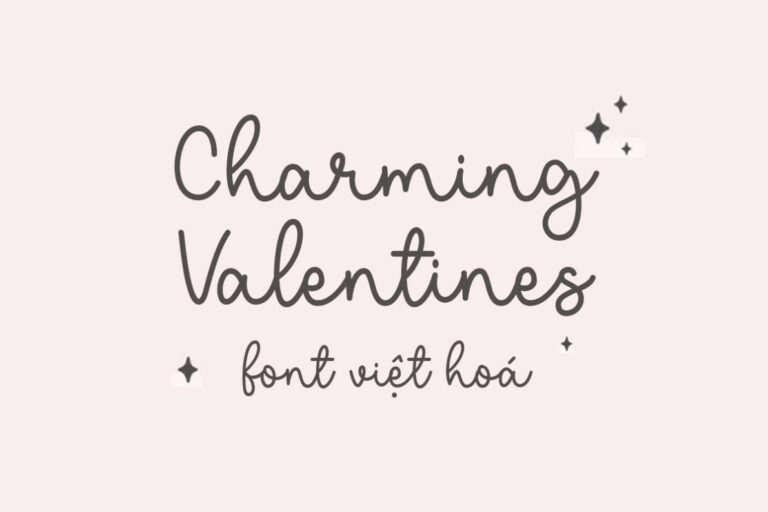
Tải Font việt hoá MJ Charming Valentines Tuyệt Đẹp Cho Thiết Kế Lãng Mạn
Giới thiệu về Font việt hoá MJ Charming Valentines
Trong thế giới đồ họa hiện nay, việc tìm kiếm một mẫu Font Chữ phù hợp để truyền tải thông điệp yêu thương là vô cùng quan trọng. Font việt hoá MJ Charming Valentines là một bộ font calligraphy hiện đại với những đường nét thanh mảnh, uốn lượn đầy tinh tế. Đây là sự lựa chọn hoàn hảo cho các bạn học sinh, sinh viên và thầy cô giáo khi muốn tạo ra những tấm thiệp chúc mừng, bài thuyết trình hay các ấn phẩm trang trí nhân dịp lễ tình nhân hoặc những sự kiện đặc biệt trong nhà trường.
Đặc điểm nổi bật của bộ font chữ
Bộ font này nổi bật với phong cách viết tay mềm mại, mang lại cảm giác chân thực và gần gũi. Điểm cộng lớn nhất là khả năng hiển thị tiếng Việt trọn vẹn, không bị lỗi dấu, giúp người dùng dễ dàng thể hiện ý tưởng mà không gặp rào cản kỹ thuật. MJ Charming Valentines còn bao gồm các ký tự thay thế và những nét móc trang trí phong phú, giúp các thiết kế trở nên bay bổng và có chiều sâu nghệ thuật hơn bao giờ hết.
Ứng dụng Font việt hoá MJ Charming Valentines trong học tập và đời sống
Với vẻ ngoài lãng mạn, Font việt hoá MJ Charming Valentines thường được sử dụng trong các dự án làm thiệp handmade, tiêu đề báo tường hoặc trang trí ảnh kỷ niệm. Các bạn học sinh có thể dùng font này để làm mới trang vở hoặc tạo ra những lời chúc ý nghĩa gửi tặng bạn bè. Trong môi trường sư phạm, giáo viên cũng có thể ứng dụng font chữ này vào các bài giảng về nghệ thuật viết chữ để khơi gợi cảm hứng sáng tạo cho học sinh.
Lưu ý khi sử dụng font trong thiết kế
Để đạt hiệu quả thị giác tốt nhất, bạn nên kết hợp font này với các tông màu pastel nhẹ nhàng như hồng, đỏ nhạt hoặc trắng. Tránh sử dụng font cho các đoạn văn bản quá dài để đảm bảo tính dễ đọc cho người xem.